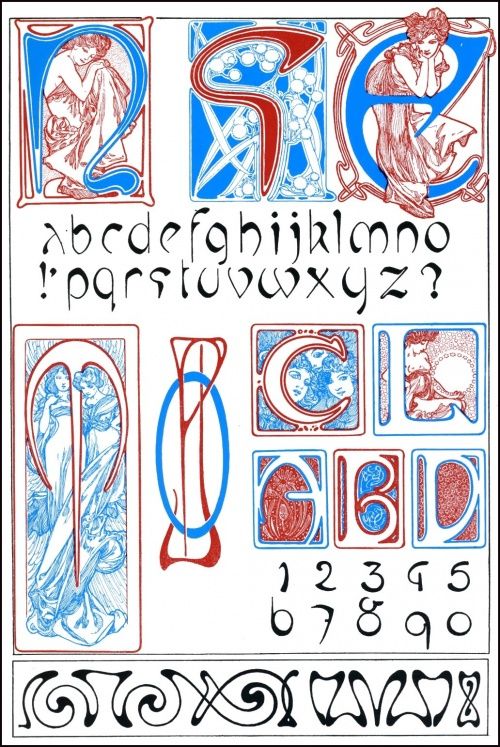
искусство модерн, Он начинается в конце XNUMX-го и начале XNUMX-го века, революционизируя художественные идеи того времени., опираясь на набор новых эстетических идеалов и стремление к современности. Это художественное движение использовало как возможности, которые предлагали новые технологии, такие как новые материалы, так и сочетание красоты и тщательности. Все это привело к идеальному союзу между архитектурой, мебелью и дизайном.
Это новое художественное движение использовало природу, женственность, использование геометрических форм и изогнутых линий, а также асимметрию в качестве ориентиров для вдохновения своих проектов. Этот декоративный стиль процветал на международном уровне на протяжении всей своей истории. Пользуясь случаем, мы не только поговорим о важности этого движения, но и Мы назовем ваши шрифты в стиле модерн, чтобы вы могли добавить их в свой типографский каталог.
графические дизайнеры и иллюстраторы того времени пытались представить искусство как элемент повседневной жизни.
Стиль модерн и его влияние на графику.
Как мы указывали в начале публикации, модерн — новое художественное течение, возникшее в конце XIX века. Он стремился развивать новое и современное искусство, основанное на природе, что можно увидеть во многих работах Альфонса Мухи. Этот новый стиль сумел добавить новую эстетическую ценность предметам повседневного обихода.
Это новое направление дизайна использовало в своих работах изогнутые линии и асимметричные композиции. Наиболее частыми мотивами, которые можно было увидеть на работах этого типа, были те, которые содержали природные мотивы, такие как листья или цветы и, конечно же, женские фигуры.
Наиболее характерной чертой этого нового движения была его адаптация к современной жизни и поиск аутентичности. Это привело к Ар-нуво расширился на различные опоры графического искусства. таких как книжные или журнальные иллюстрации, плакаты, декоративные панно, обои, гравюры и даже печатные рисунки.
Некоторые из наиболее важные фигуры этого движения Они были,
Муха был не единственной важной фигурой в модернизме, но и другие художники, такие как Чарльз Ренни, Коломан Мозер, Александр Штайнлер, Жюль Шере, И многие другие.
Характеристики типографики в стиле модерн
Во времена, когда модерн был в самом разгаре, дизайн плакатов был очень распространен и распространялся в больших количествах. Из-за этого нового стиля, начал развиваться стиль типографики и письма, типичный для этого движения.
Выделите одну из самых фундаментальных фигур модерна, такую как Уильям Моррис. Это было ключевым в декоративно-прикладное искусство в мебели или окнах, в дополнение к его значение в графическом дизайне и типографике.
Многие художники, принадлежащие к этой эпохе, предпочитали создавать собственные шрифты посредством ручного письма, отходя от шрифтов того времени. Эти ручные шрифты придавали уникальный и индивидуальный аспект.
Вот почему может быть трудно определить конкретные шрифты того времени, но можно назвать общие и конкретные аспекты используемых шрифтов.
В типографике, используемой в стиле модерн, выделяется использование орнаментов в буквах. Они были вдохновлены такими темами, как природа, для дизайна персонажей. Использовались органические линии, где преобладали кривые.
Типографика, нарисованная на плакате, должна была быть связана с иллюстрацией, добавленной на этот носитель. А именно, типографика работала как элемент союза с формами, которые имело изображение. Создается визуальный маршрут, гармоничный, поскольку все элементы интегрированы.
Типографика воспринималась больше, чем как текст, как еще одно изображение композиции.. Между знаками давался больший интервал. Искали не только хороший дизайн, но и визуальную асимметрию. Для этого стиля было характерно добавление к композициям декоративных мотивов модерна.
Шрифты в стиле модерн
Если вы ищете шрифты, которые сочетают в себе романтический и витиеватый стиль модерна, вы находитесь в правильном месте.
Сегодня мы поделимся с вами некоторыми лучшие шрифты, вдохновленные этим художественным движением.
Вискамонта
Элегантный шрифт без засечек в стиле модерн, конец XNUMX века. Шрифт, который хорошо работает в заголовках или в качестве основного элемента плакатов, обложек, текстиля и т. д.
Цавеласт
Оригинал и вдохновлен эстетикой произведений Альфонса Мухи, этот шрифт соответствует стилю этого движения в каждом из своих символов. Этот мощный шрифт включает прописные буквы, знаки препинания, цифры и многоязычную поддержку.